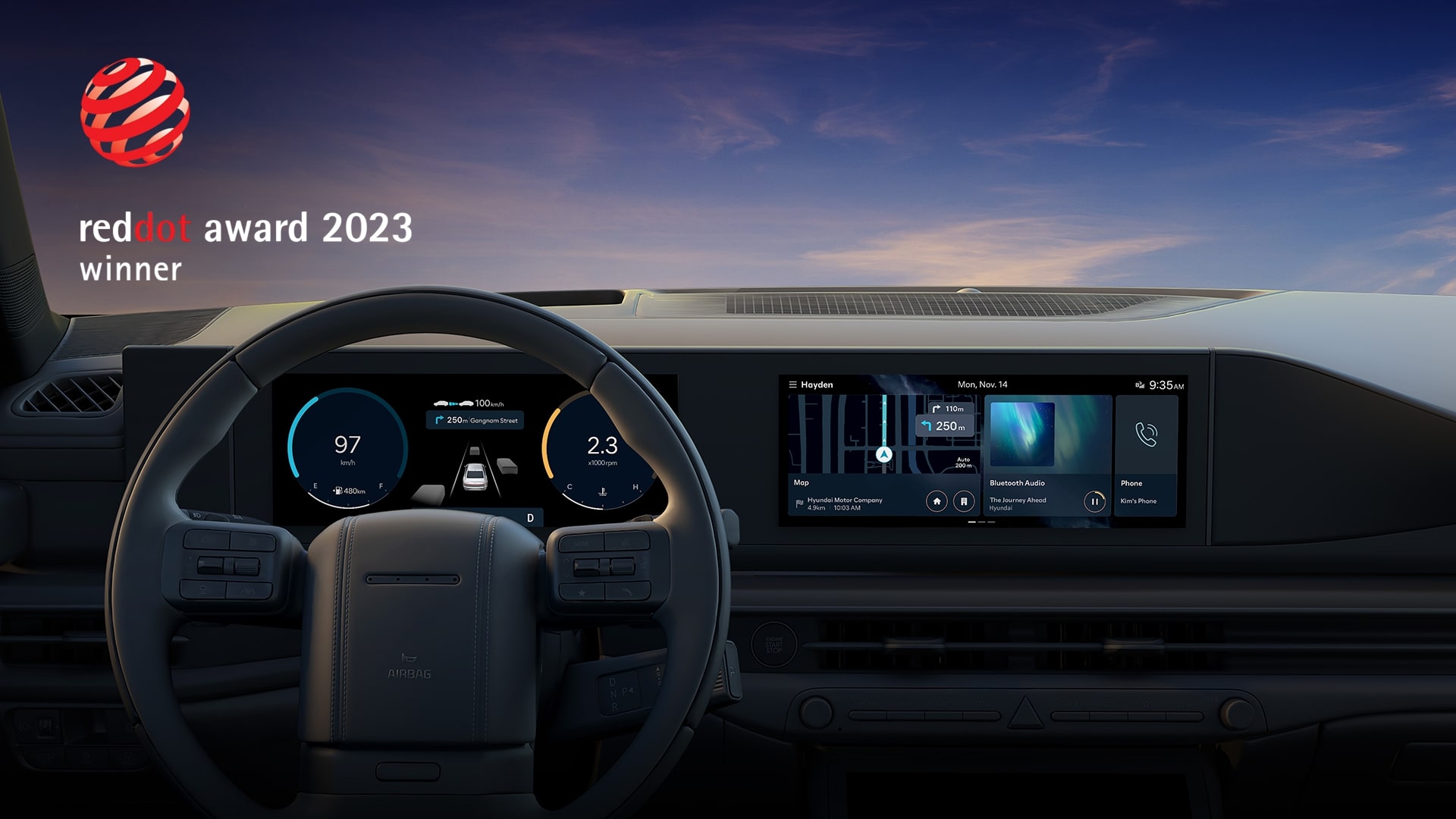
Hyundai premiata con Red Dot Design Award per il sistema infotainment Seon e il suo font
Hyundai si è aggiudicata i tre riconoscimenti Red Dot Award 2023 con il concept N Vision 74, il sistema di infotainment di nuova generazione “Seon” e il font digitale Hyundai Sans UI.
Hyundai premiata ai Red Dot Design Award per sistema di infotainment Seon e per font Hyundai Sans UI
L’azienda è stata premiata anche nella sezione Brands & Communication Design 2023 per il suo sistema di infotainment Connected Car Navigation Cockpit (ccNC) e il suo nuovo font digitale.
Premiato nella categoria Interface & User Experience Design, “Seon” (“Linea” in coreano), vanta un design nuovo applicato al sistema di infotainment ccNC di Hyundai. Ispirandosi al motivo delle linee orizzontali esistenti in natura, l’azienda riferisce di avere sviluppato “Seon” partendo da piccoli componenti grafici per arrivare all’intero display completando lo stile grafico semplice e essenziale . Questo concetto grafico è stato progettato per armonizzarsi con il design interno ed esterno dei veicoli e per favorire la coerenza tra i display.
Il sistema di infotainment ccNC di Hyundai sfrutta un sistema a griglia. gli schemi di funzionamento sono pensati per facilitare l’utilizzo da parte dei conducenti durante la guida, promettendo usabilità ottimale e un’esperienza utente sempre coerente.
Hyundai premiata ai Red Dot Design Award per sistema di infotainment Seon e per font Hyundai Sans UI
Nella categoria Typography, infine, è stato premiato Hyundai Sans UI. Il font digitale UX per la mobilità dell’azienda è stato progettato pensando alle caratteristiche di user experience della mobilità ma anche alle funzionalità del software basate su criteri di estetica, leggibilità e identità del brand.
Il produttore riferisce che Hyundai Sans UI eredita le caratteristiche di design del font del marchio Hyundai (Hyundai Sans) e promette “leggibilità ottimale in varie situazioni di guida”. In termini di struttura visiva, Hyundai Sans UI supporta caratteri tipografici diversificati, oltre al corsivo, e attraverso l’ordine gerarchico del sistema UI consente di visualizzare e comprendere rapidamente anche informazioni complesse.
Hyundai premiata ai Red Dot Design Award per sistema di infotainment Seon e per font Hyundai Sans UI